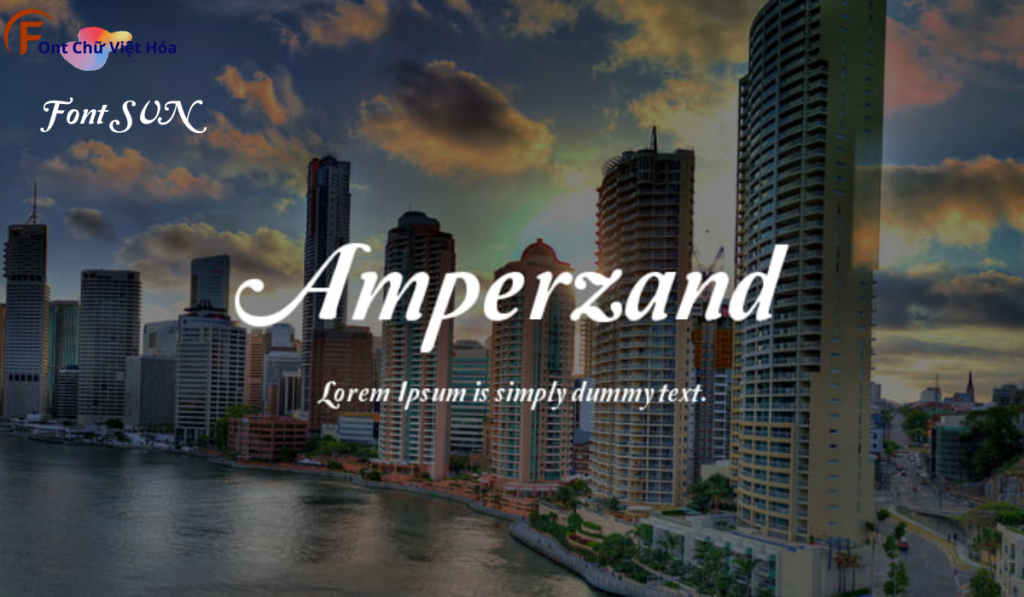
Font SVN – Amperzand Việt Hóa
Font SVN-Amperzand Việt Hóa
Tác giả: SVN-Amperzand
Kiểu chữ: Chữ không chân
Font SVN-Amperzand Việt Hóa là một font chữ không chân cá tính, thuộc bộ font SVN. Được thiết kế với mục tiêu mang lại sự độc đáo và sáng tạo, font này lý tưởng cho các dự án thiết kế như logo, poster, và bao bì sản phẩm. Với các nét chữ sắc nét và độ dày đều đặn, Font SVN-Amperzand Việt Hóa không chỉ dễ đọc mà còn tạo cảm giác hiện đại và phá cách. Việc Việt hóa font giúp người dùng dễ dàng sử dụng trong các thiết kế tiếng Việt, mang lại sự tiện lợi và thẩm mỹ cao.